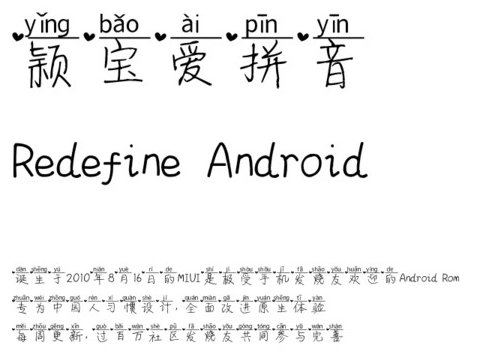
穎寶愛拼音體是一款為趙麗穎粉絲制作的拼音字體,不僅有著標(biāo)準(zhǔn)的拼音注釋,而且還增加了可愛的愛心符號(hào),讓文字更加活潑,充滿愛心,喜歡的朋友就來綠色資源網(wǎng)試試吧!
穎寶愛拼音,是在穎寶情書體的基礎(chǔ)上,加上拼音等裝飾內(nèi)容,可愛且顯示效果萌萌噠。
穎寶愛拼音體是可可字體的一款可愛卡通字體,由設(shè)計(jì)師子盟制作分享,讓穎寶的粉絲可以使用這款字體與偶像親密互動(dòng),本字體是在情書體上進(jìn)行修飾而來,情意深刻!